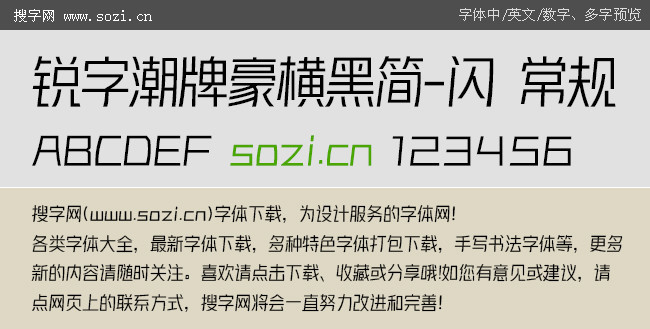
銳字潮牌豪橫黑簡(jiǎn)-閃 常規(guī)
搜字網(wǎng)提供一款銳字潮牌豪橫黑簡(jiǎn)-閃 常規(guī)中文字體下載,銳字潮牌豪橫黑是銳字字庫(kù)推出的一套個(gè)性藝術(shù)字體,共5個(gè)字重,字體穩(wěn)定,優(yōu)雅,堅(jiān)固,看起來(lái)非常漂亮,整體效果非常均勻,字符齊全,可以廣泛使用,可用于出版和印刷,文學(xué)雜志,海報(bào)設(shè)計(jì)等應(yīng)用。(本字體為個(gè)人非商用版,商用請(qǐng)聯(lián)系作者購(gòu)買(mǎi)授權(quán))